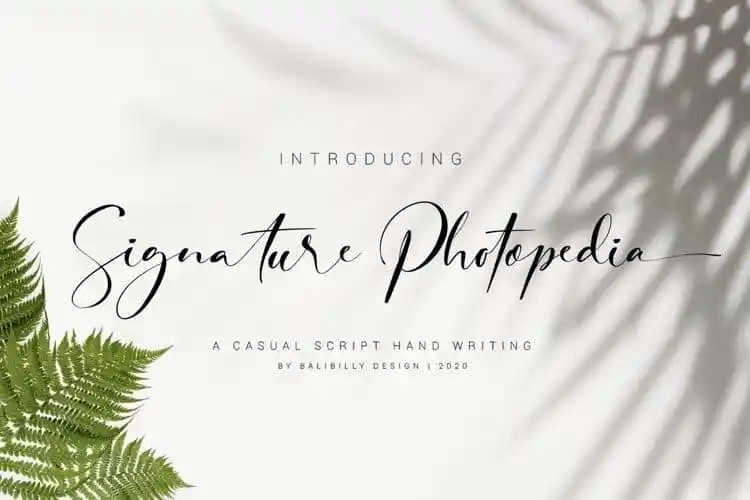
Signature Photopedia Script Font
Signature Photopedia Script Font é uma fonte de estilo script inspirada nos murais urbanos ou freestyle. Inspirado na arte urbana, esta fonte oferece um estilo casual ou marcador com muitas alternativas estilizadas que permitem criar cabeçalhos realistas e detalhados. O designer 99designs trabalhou meticulosamente para tornar a fonte acessível e versátil, incluindo uma vasta quantidade de alternativas estilizadas letras, ligaturas únicas e belos desenhos em pontos abertos do tipo. Esta é uma excelente opção para quem busca criar texturas vibrantes e sofisticadas para aplicativos como editoriais de mídia social, anúncios digitais ou materiais de design gráfico moderno.